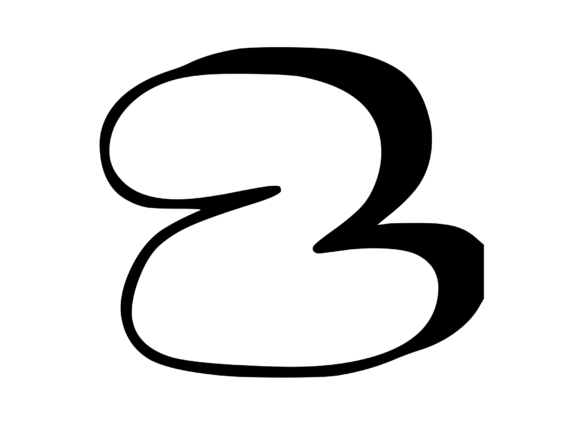
Friendly Shaded Comic Hand Drawn Mono Z
Het vinden van de juiste ontwerpelementen kan lastig zijn, maar Friendly Shaded Comic Hand Drawn Mono Z biedt een uitzonderlijke collectie die uw werk direct naar een hoger niveau tilt.